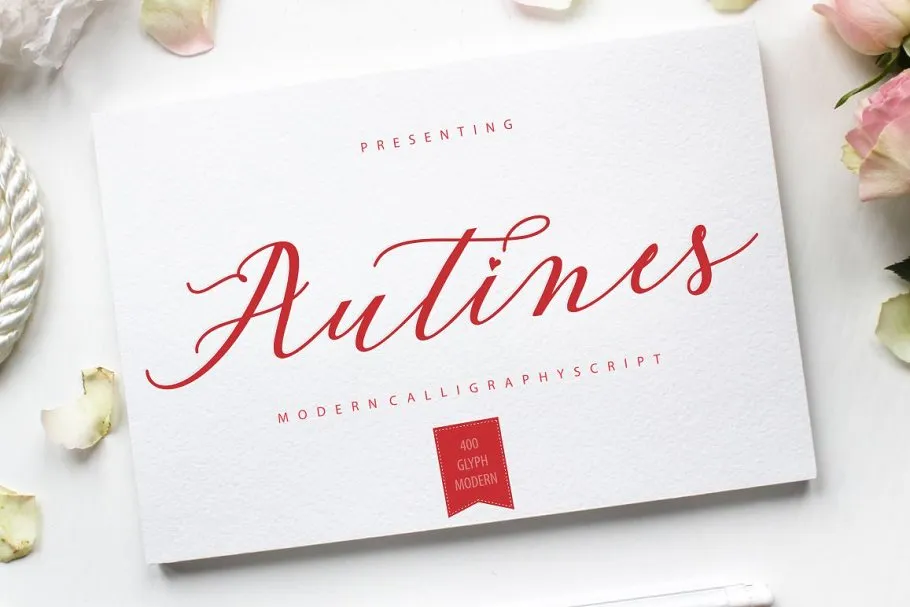
Autines Script Font – Download Grátis
A autenticação Autines Script Font é uma elegante letra moderna feminina que oferece um toque sofisticado ao seu design digital. Este novo tipo de caligrafia moderna traz a sensação única do designer original. Seja para criar cartões de aniversário ou embalagens, ideias criativas para marcas ou desenhos de arte, autógrafos e convites, ou mesmo para estampar roupas e sapatos. A Autines Script Font será perfeita para projetos como fotografias, marcos nas imagens, citações no blog, cabeçalhos em posters, casamentos e identidade corporativa. Com seu estilo de script moderno, esta fonte oferece uma variedade única de padrões e formas. Está disponível para personalizar qualquer projeto digitado ou impresso com a sensação sofisticada que você deseja. Seja um texto informativo para o blog, uma citação inspiradora para um convite especial ou uma marca perfeita para as suas roupas – tudo isso e muito mais é possível graças à Autines Script Font.
Designer: beacon